「平成インターネット」の雰囲気にぴったりな日本語フォント
今回は、懐かしくて少しチープ、でもなぜか愛おしい「平成インターネット」の雰囲気にぴったりな日本語フォントをご紹介します。
平成インターネットといえば、個人サイト、掲示板、ブログパーツ、キリ番文化、点滅するバナー、原色のグラデーション、ドット絵やデコメのようなにぎやかな空気感。今見ると少し粗くて不完全だけれど、その手作り感や過剰な装飾こそが、当時のWebらしい魅力でもあります。
今回は、ドット風、デジタル風、レトロゲームっぽいフォントなど、平成初期〜平成中期のインターネット感を演出できる日本語フリーフォントをピックアップしました。懐かしくてちょっと不思議なWebデザインや、レトロポップなビジュアル制作にぜひ活用してみてください。
懐かしくてクセになる。平成インターネット風の日本語フリーフォント特集
以下のサンプルのように、「平成インターネット」な雰囲気にぴったりなフォントをご紹介します。ガラケー時代のWebサイトやブログ、掲示板文化、個人サイト、ゲーム画面、初期のデジタル表現などにぴったりなフォントです。
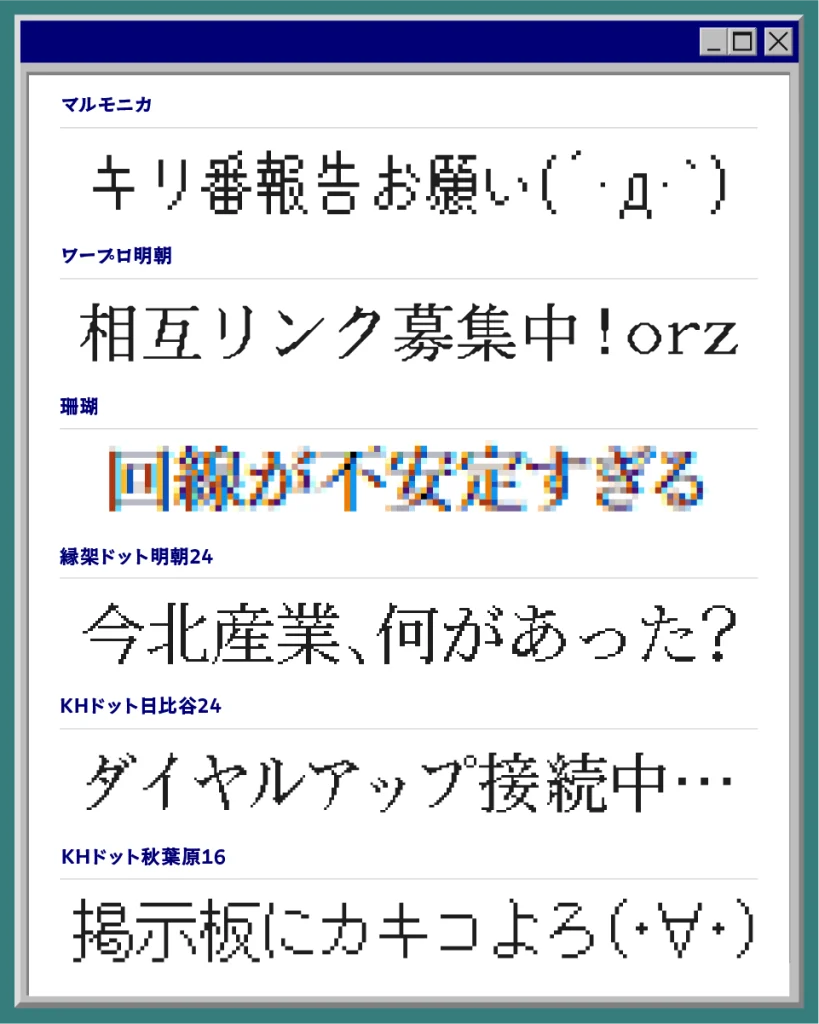
珊瑚(sango)
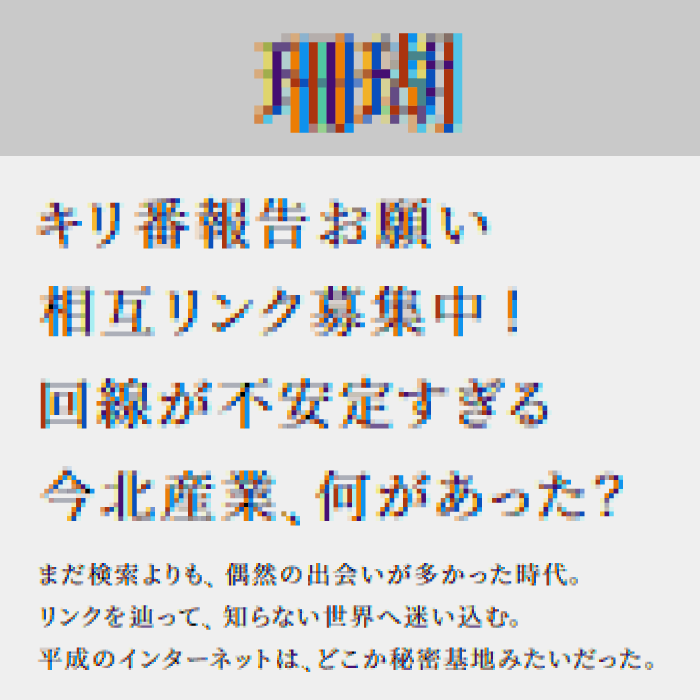
| 活用シーン例 | 平成インターネット、グリッチデザイン、掲示板風バナー、電脳世界、レトロデジタル表現 |
珊瑚(sango)は、RGBがずれたようなグリッチ表現が特徴的で、平成初期のネットカルチャーやブラウン管越しの不安定なデジタル感を思わせるフォントです。
どこかバグや通信障害を連想させる独特のノイズ感があり、インターネット黎明期らしい“怪しさ”や“カオス感”を演出したいデザインにぴったりなフォントです。
縁架ドット明朝
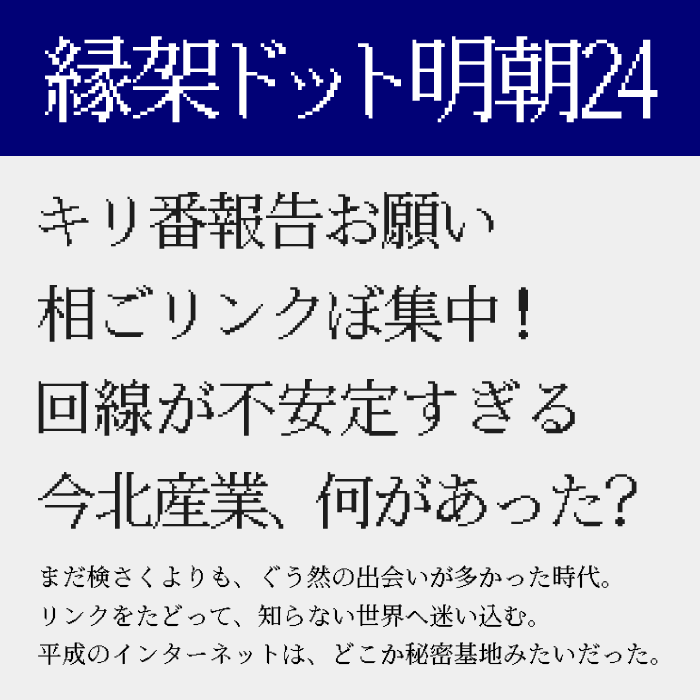
| 活用シーン例 | 個人サイト風デザイン、平成Webカルチャー、テキストサイト、レトロPC表現 |
縁架ドット明朝24は、ドットフォント特有の無機質さと明朝体の上品さを掛け合わせたフォントです。昔の個人サイトやテキスト中心だった平成インターネットの空気感をそのまま切り取ったような印象があり、懐かしいネット文化や古いWebページを再現したい場面で活躍します。
ワープロ明朝
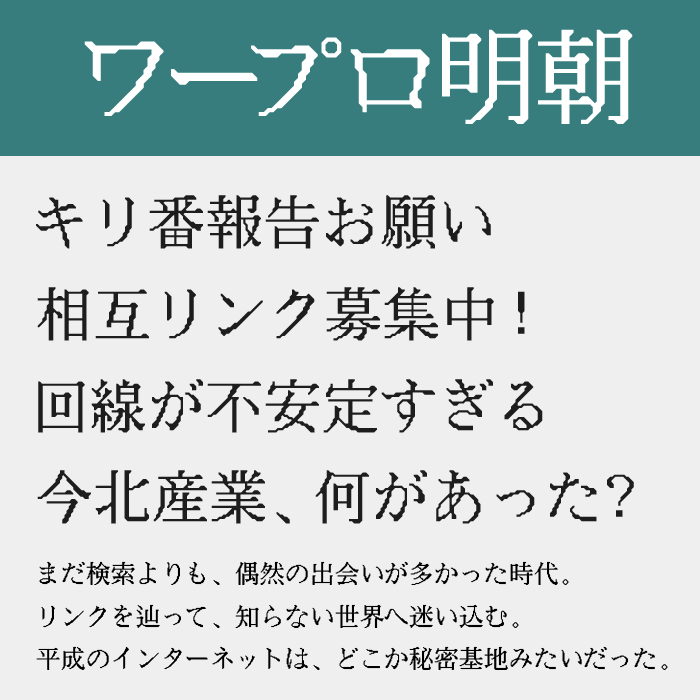
| 活用シーン例 | ワープロ風デザイン、昔のPC文化表現、平成デジタル表現、ノスタルジックデザイン |
ワープロ明朝は、その名前通り昔のワープロ専用機で表示されていたような独特の輪郭を持つフォントです。
平成初期のオフィス機器や古い文書ソフトを思わせる懐かしさがあり、インターネット普及前後のレトロPC文化を感じさせます。少し無骨で独特なデジタル感が魅力のフォントです。
DotGothic16
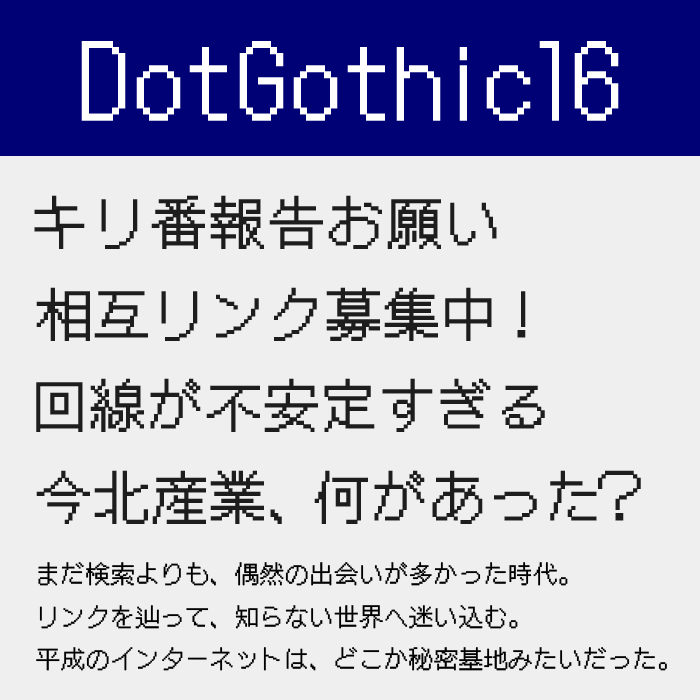
| 活用シーン例 | レトロゲーム風デザイン、初期PC風UI、ピクセルアート、懐かしいネット表現、ドットデザイン |
DotGothic16は、昔のゲーム機や初期パソコンのUIを連想させる、王道のドット系フォントです。
視認性の高いシンプルなデザインながら、どこか懐かしいデジタル感をしっかり持っており、平成インターネットらしいチープで親しみある空気感を自然に表現できます。
フォント名
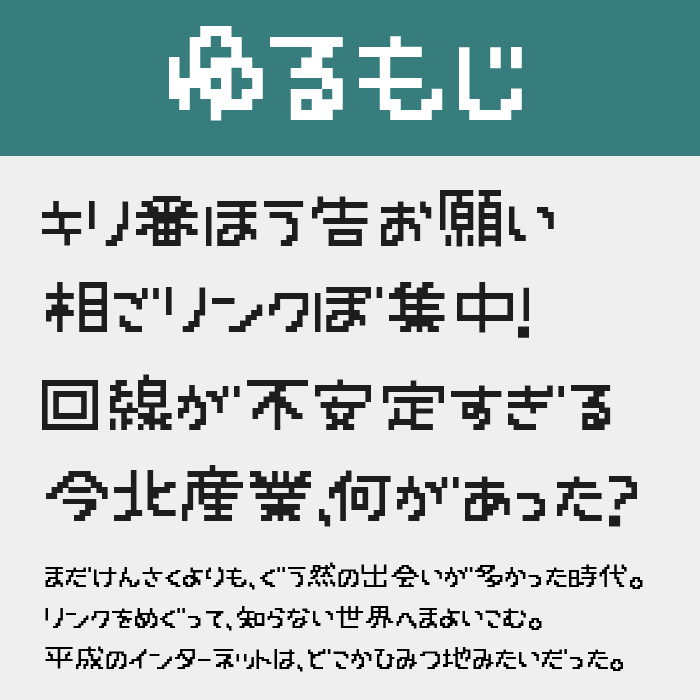
| 活用シーン例 | 個人ホームページ風、手作りサイト風デザイン、懐かしいネット文化、ドットデザイン |
ゆるもじは、ドットフォントの無機質さを残しながらも、少し柔らかく手作りっぽい雰囲気を持ったフォントです。
平成時代のホームページビルダーで作られた個人サイトや、素朴で手作り感のあるWebデザインを思わせる空気感があり、どこか懐かしく温度感のあるインターネット表現におすすめです。
こんてにゅー2P
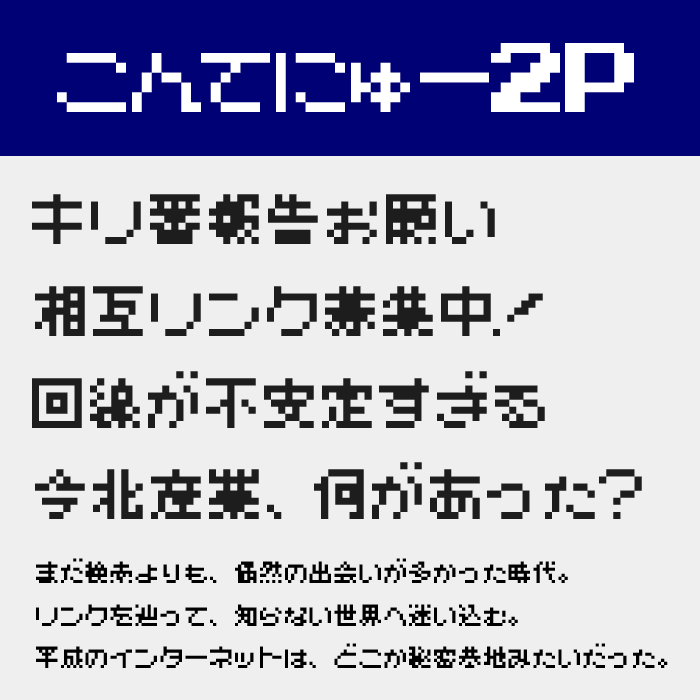
| 活用シーン例 | ゲームサイト風デザイン、2ちゃんねる風表現、レトロゲームUI、ドットバナー制作、平成ゲーム文化 |
こんてにゅー2Pは、ゲームボーイやファミコン時代を思わせる、クラシックな2P風ドットフォントです。
平成インターネットとゲームカルチャーが密接だった時代の空気感をそのまま感じられ、どこかアングラ感のある昔のWebコンテンツやゲーム系サイトの表現にもぴったりなフォントです。
ベストテンFONT
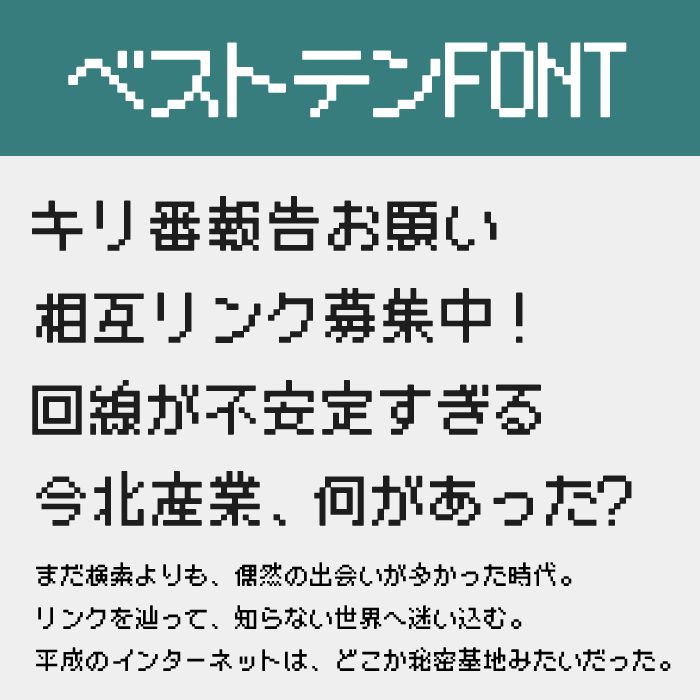
| 活用シーン例 | 昔の掲示板風デザイン、レトロPC画面、初期Webカルチャー、平成レトロ制作 |
ベストテンFONTは、粗めのピクセル感が特徴的な、古いパソコン画面を思わせるフォントです。
平成初期のネット掲示板や昔のゲーム攻略サイトなど、まだ洗練されていなかったインターネット文化を強く感じさせます。どこか不完全でチープな雰囲気が逆に味になる、平成ネット感たっぷりのフォントです。
KHドット日比谷
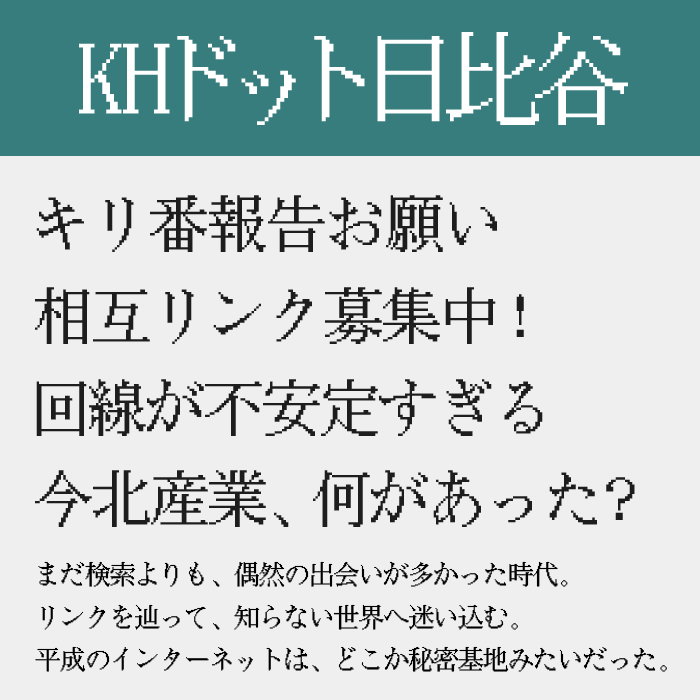
| 活用シーン例 | テキストサイト風、ガジェット系デザイン、デジタルカルチャー |
KHドット日比谷は、繊細なドット表現と少しシャープな造形が特徴のフォントです。平成インターネットの中でも、やや洗練されたテキストサイトやガジェット系コンテンツを思わせる雰囲気があり、どこか硬派で静かなデジタル感を演出できます。懐かしさとスタイリッシュさのバランスが魅力です。
マルモニカ
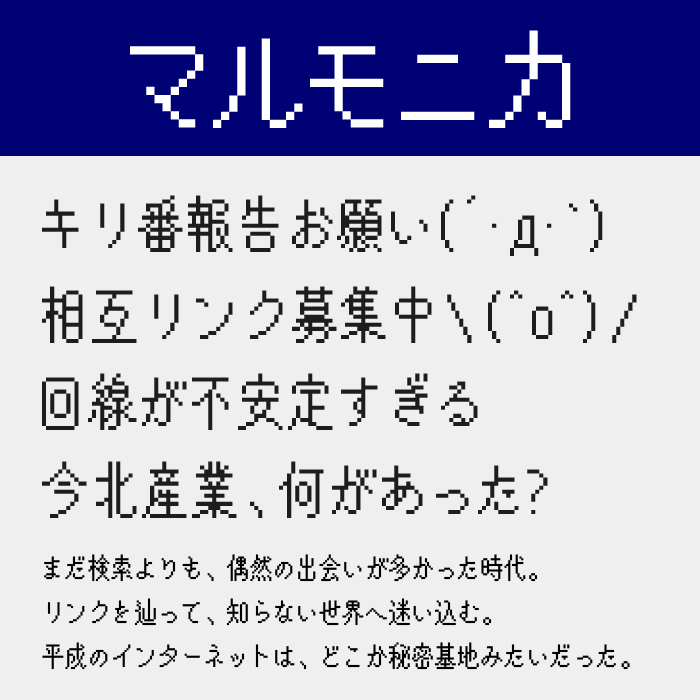
| 活用シーン例 | 顔文字文化、個人サイト風、平成ネットカルチャー、懐かしいインターネット表現 |
マルモニカは、丸みを持たせたドット表現が特徴的な、かわいらしさのあるフォントです。平成インターネット文化の中でも、掲示板や個人ホームページにあった顔文字文化やポップなネット空間を連想させます。少しゆるく、遊び心のある“あの頃のネット”を表現したいときにぴったりです。